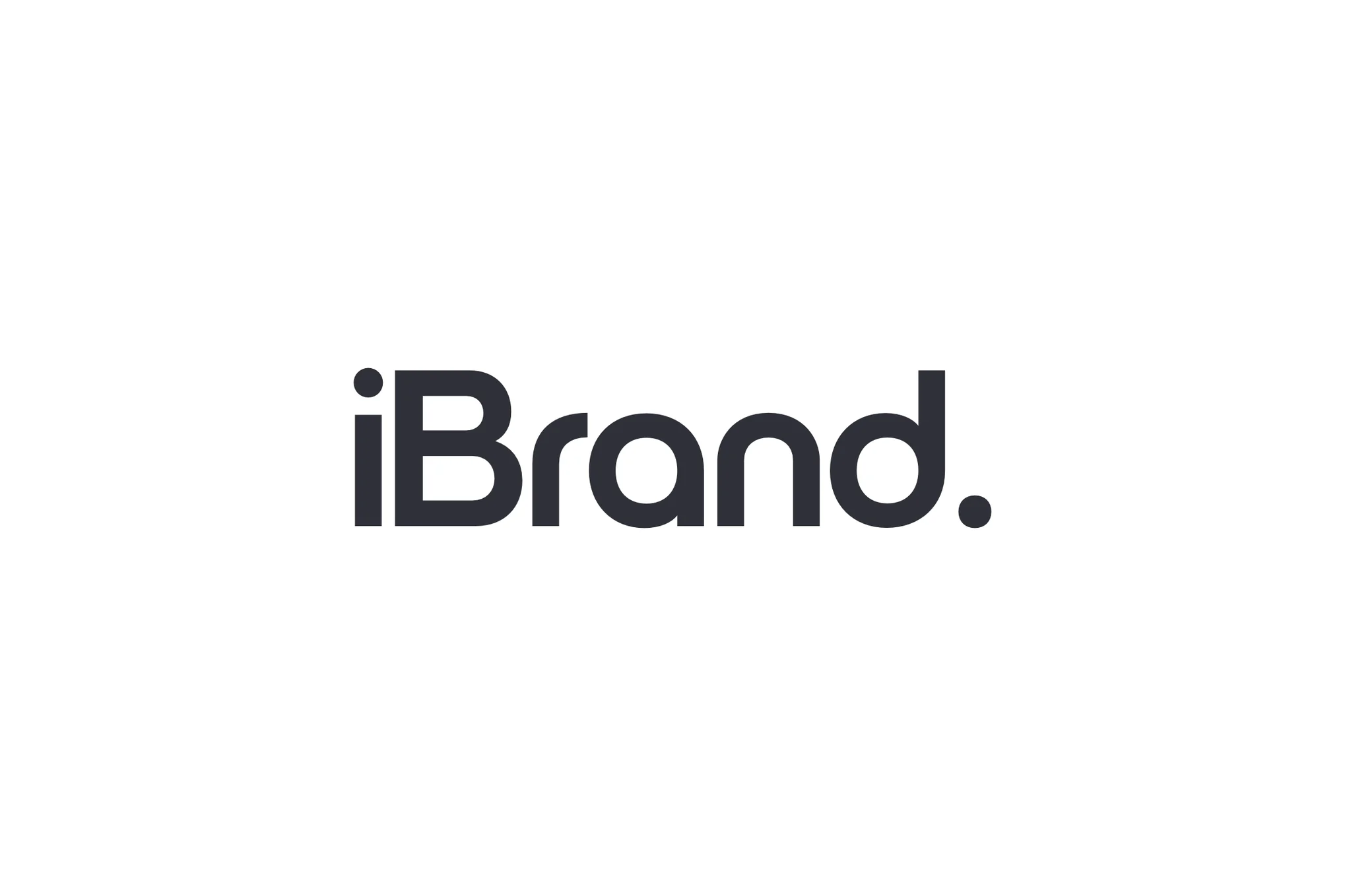
فونت iBrand یک نوع تایپ با دقت ساخته شده است که به طور خاص برای لوگوها، نام تجاری، هدرها و عنوان ها طراحی شده است. فونت iBrand با ترسیم و فاصله گذاری دقیق برای لوگوهای تاثیرگذار و مواد برندسازی، تضمین می کند که طرح های شما تاثیر ماندگاری داشته باشند. لطفاً توجه داشته باشید، فونت iBrand برای متن بدنه مناسب نیست، اما در کاربردهای بصری که در آن هر جزئیات مهم است، عالی است. پروژه های طراحی خود را با فونت iBrand امروز ارتقا دهید.